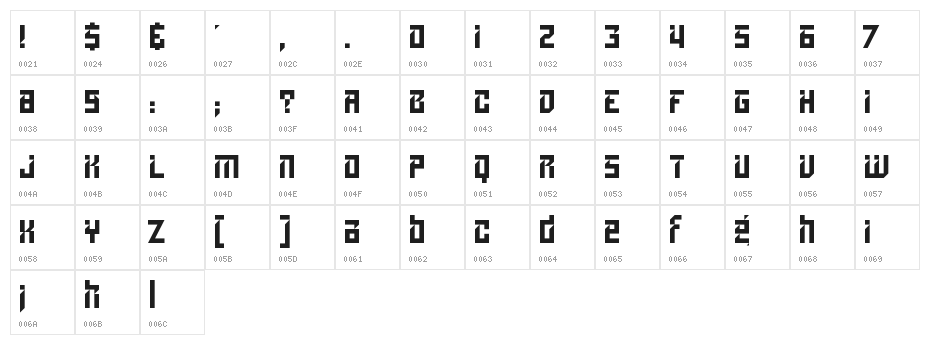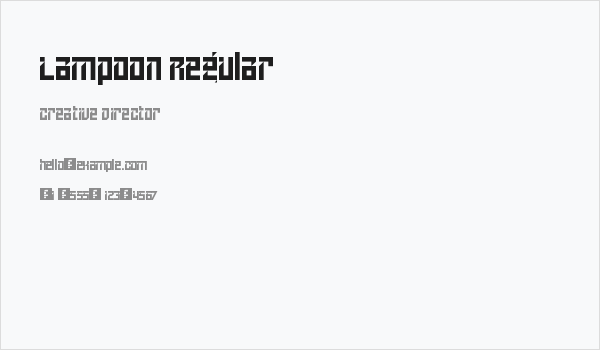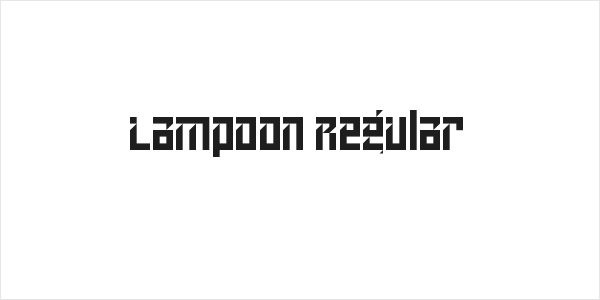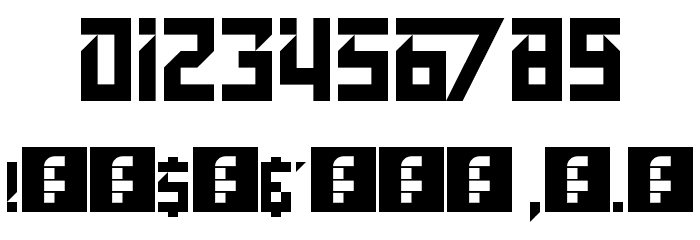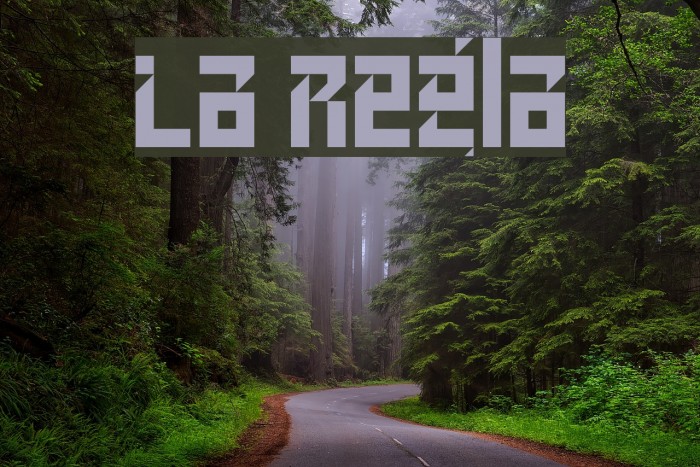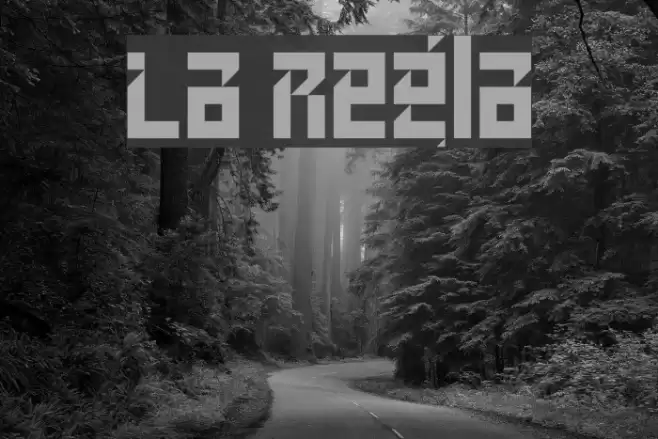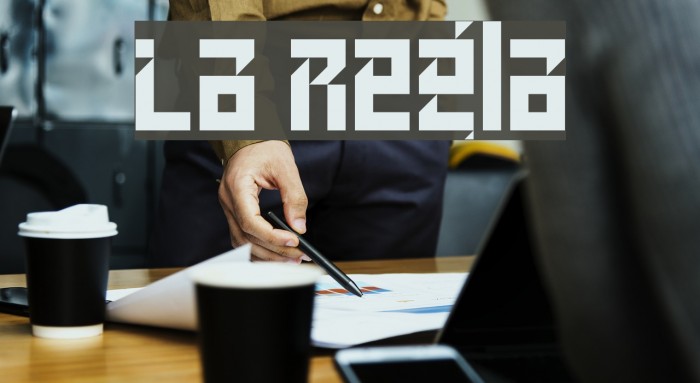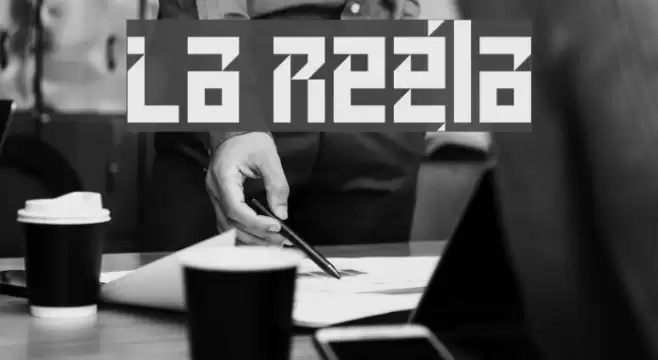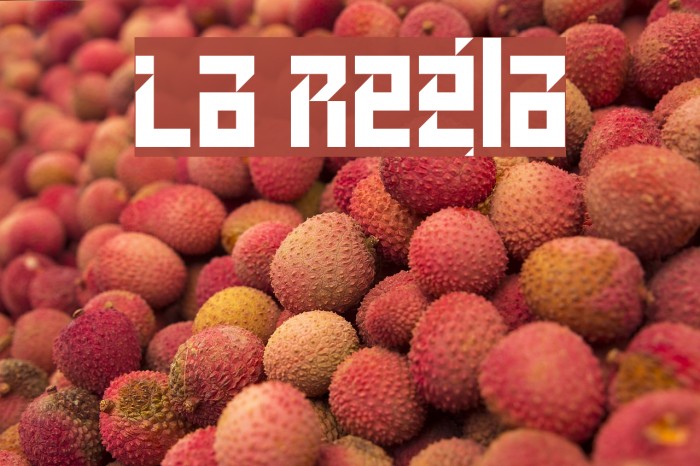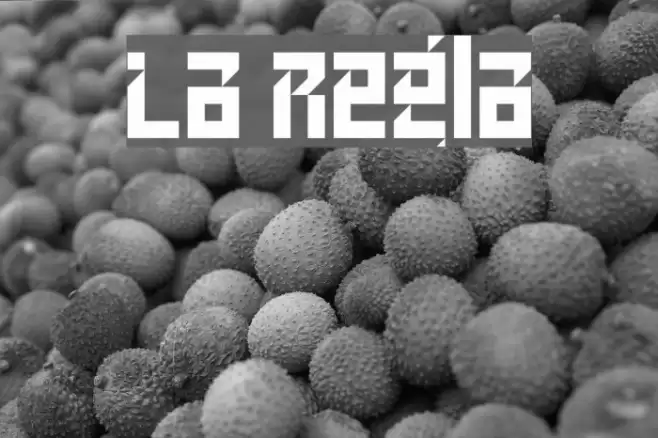
Lampoon Regular Font
| Projets proposés | Ideal for digital artwork, modern posters, video game graphics, and branding that requires a bold statement. |